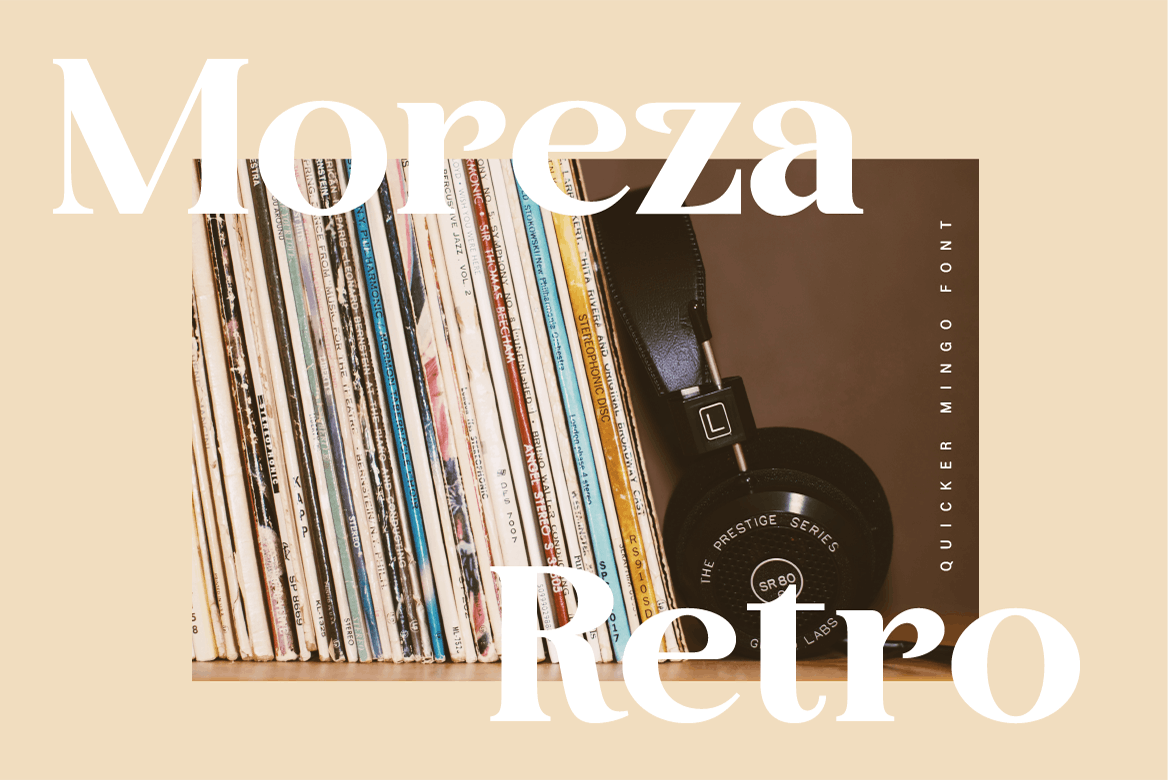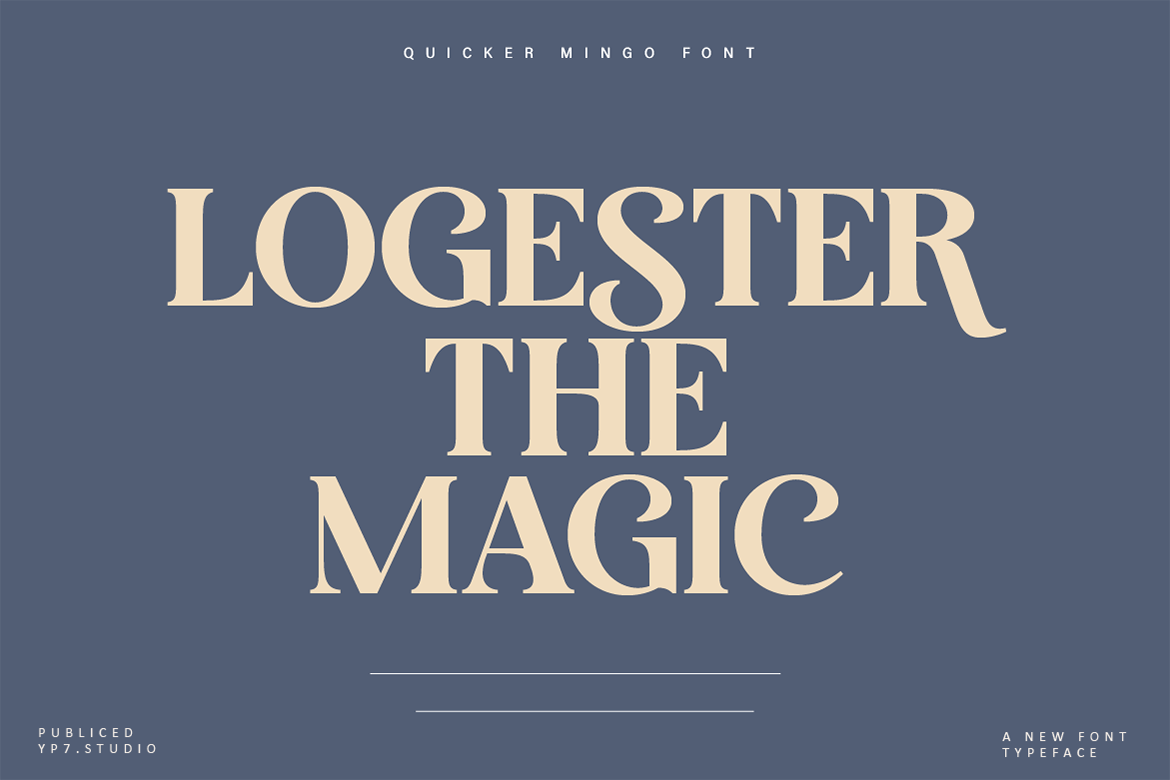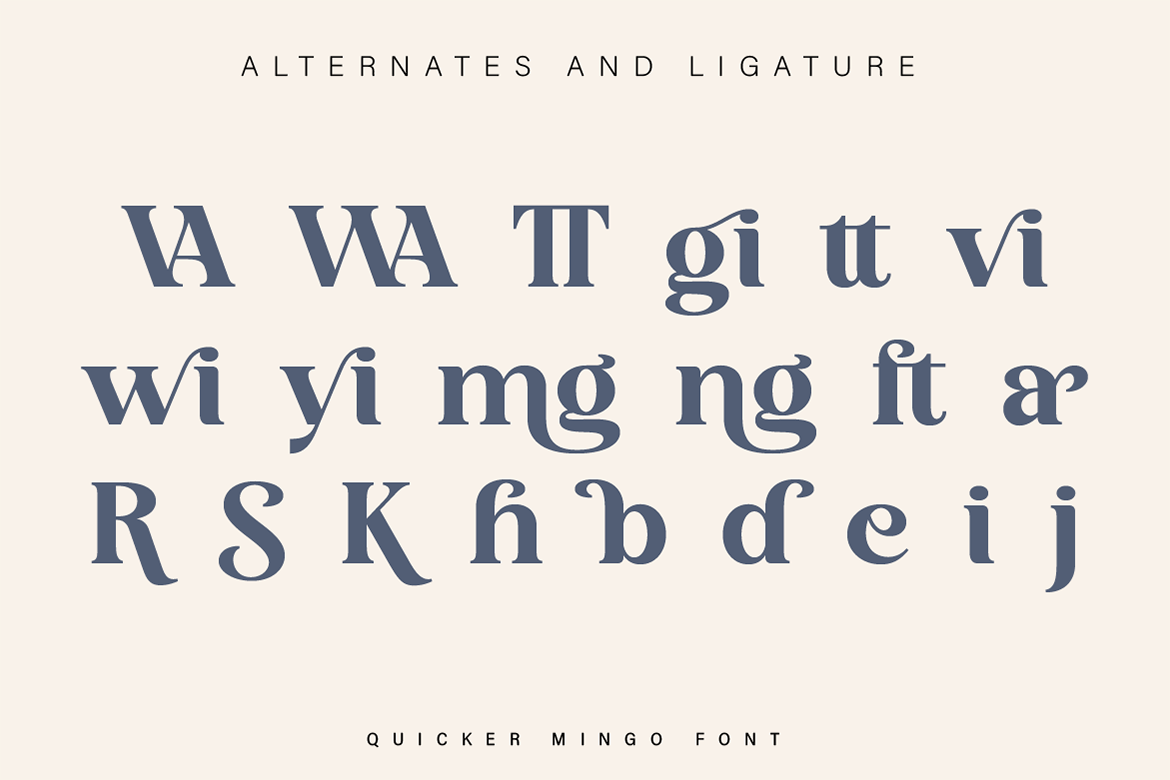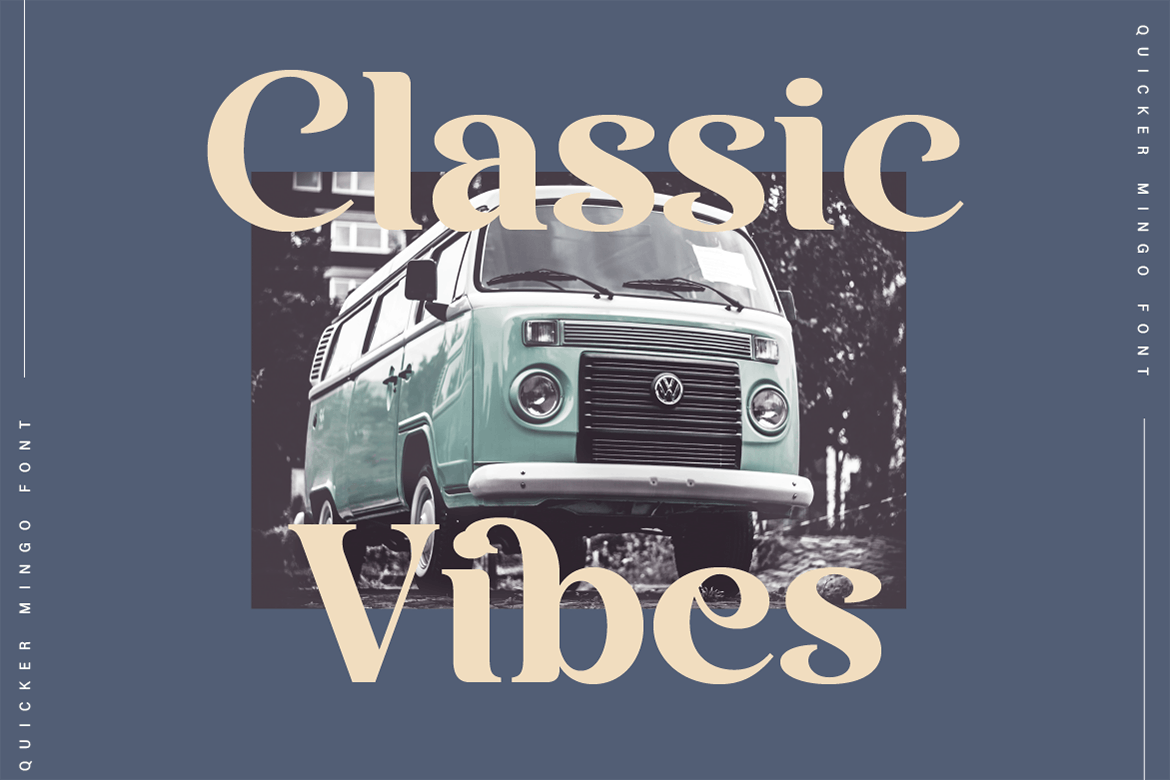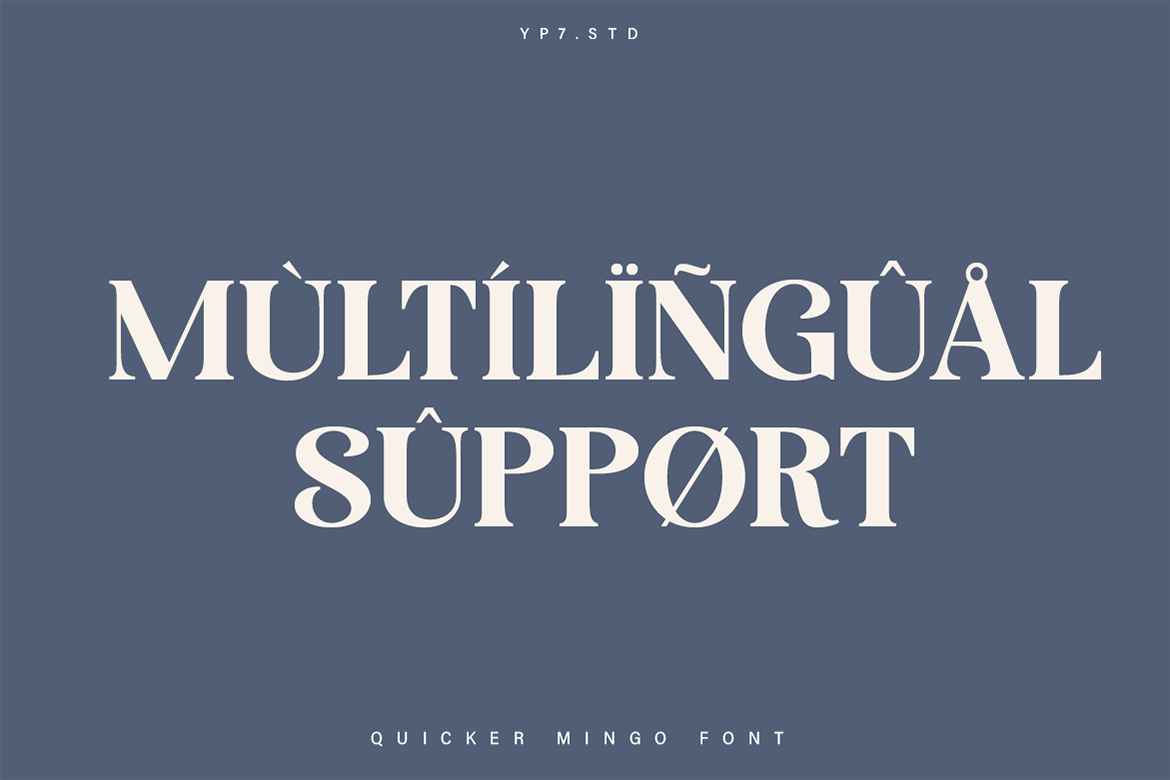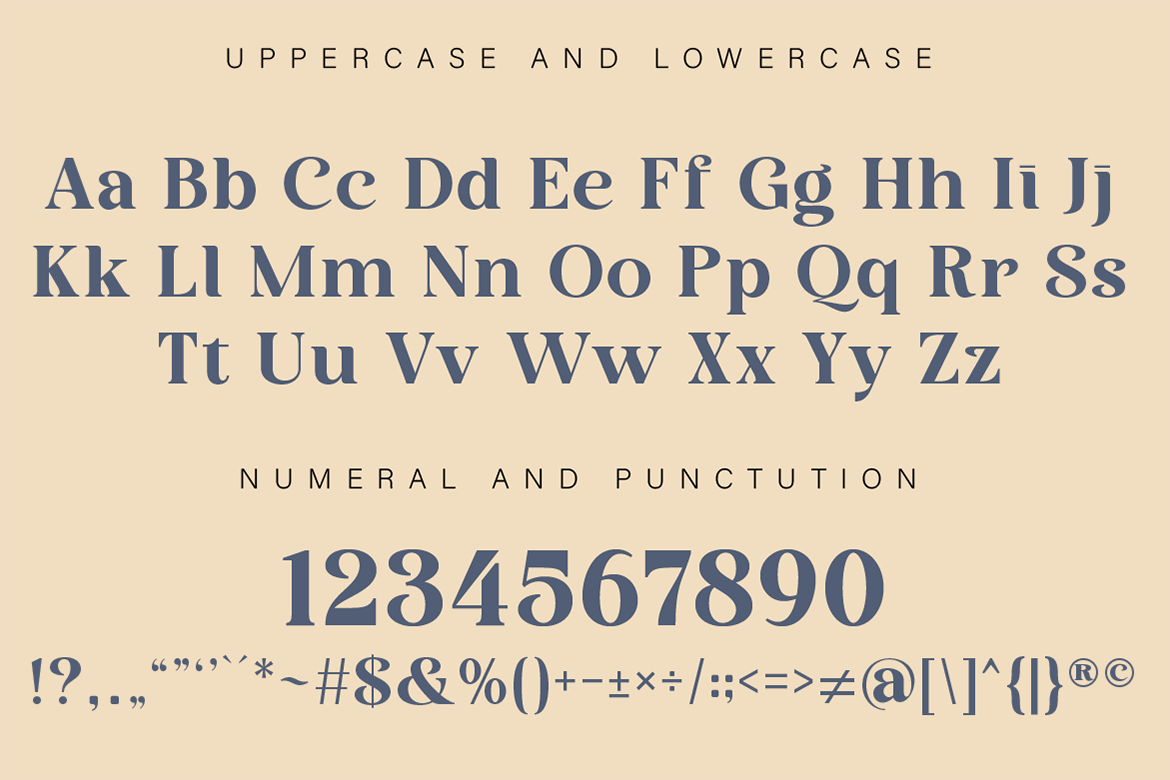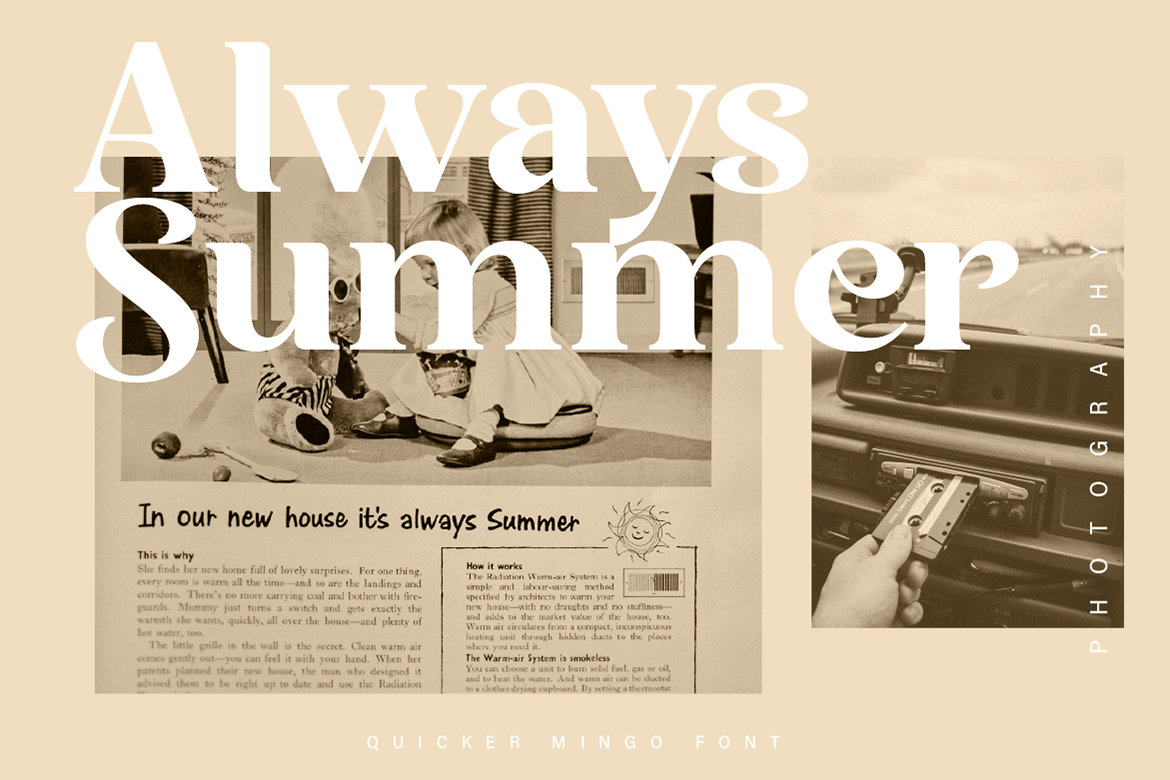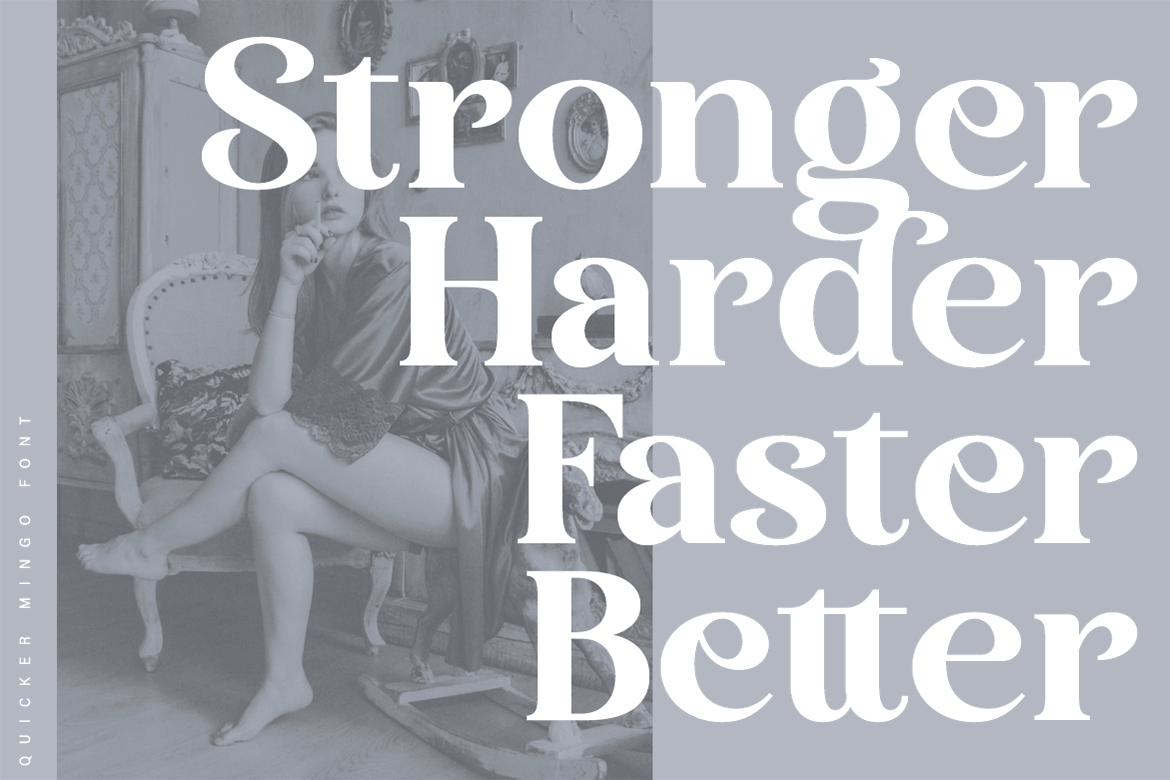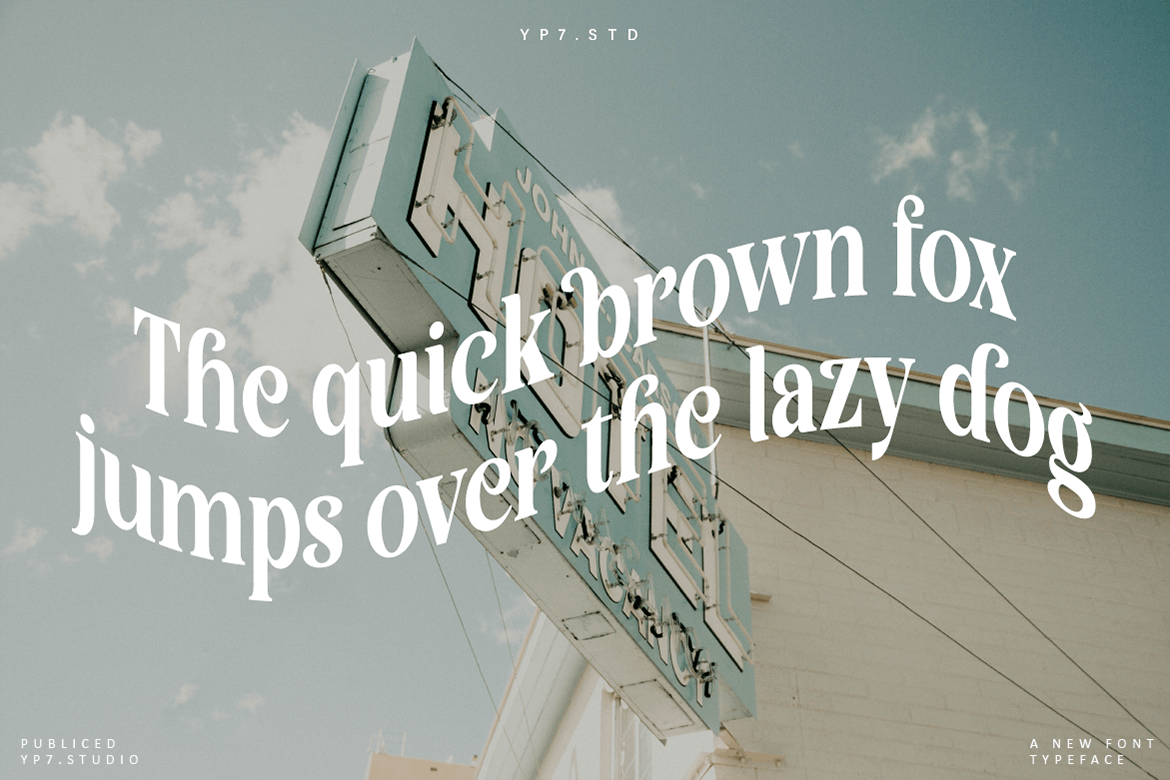
دانلود فونت مدرن رتروا برای طراحی‌های خاص
Modern Retro Font
این فونت مدرن رتروا با طراحی منحصر به فرد، گزینه‌ای عالی برای پروژه‌های شماست.
فونت مدرن رتروا یک انتخاب بی‌نظیر برای طراحان است که به دنبال ترکیب زیبایی و کارایی هستند. این فونت با طراحی خاص خود، به پروژه‌های شما جلوه‌ای جذاب و مدرن می‌بخشد.
• حروف بزرگ و کوچک
• اعداد و نشانه‌گذاری